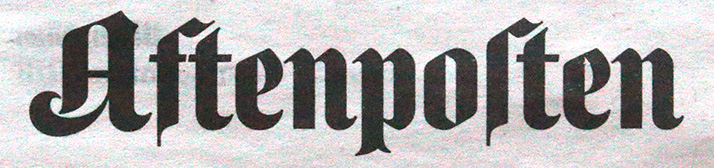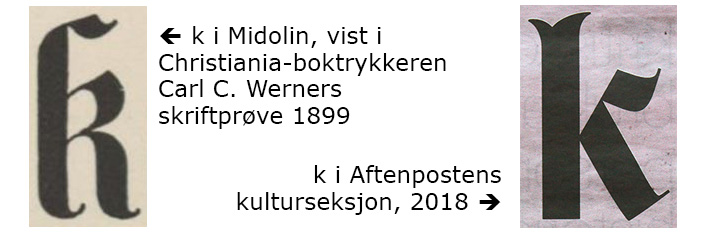
Ane Thon Knutsen disputerte for sin doktorgrad med tittelen over, 18. juni 2019 på Kunsthøgskolen i Oslo. Doktorgraden er av kategorien «Kunstnerisk utviklingsarbeid».
Doktorgradsarbeidet tar utgangspunkt i den britiske forfatteren Virginia Woolf, som i 1917 skrev novellen A Mark on the Wall, samtidig som Woolf lærte seg selv å sette tekst med blytyper i sitt eget trykkeri.
Novellen ble ifølge Ane nærmest skrevet fra settekassen og opp, og i doktorgradsarbeidet har hun utforsket hvordan litteraturen er påvirket av typografien.
Ane har som Woolf skapt sitt eget lille boktrykkeri, og som en del av oppgaven har hun håndsatt hele Woolfs novelle med store maskinfreste løse typer og trykt den på 1837 papirark (bildet). En annen likhet mellom Woolf og Thon Knutsen er deres stilling som kvinner i et (tidligere) mannsdominert fag.
Ved å klikke på en svart hånd øverst til venstre på skjermbildet på hennes nettsted kan man se trykkeprosessen og få tilgang til en 30 min. lydbok hun har spilt inn.
Thon Knutsen er utdannet grafisk designer og hennes mastergrad var også knyttet til boktrykket – som er den tradisjonelle betegnelsen på setting og trykking med løse typer. Dette tradisjonsrike håndverket kalles nå, også i Norge, for «letterpress». Anes praksis plasseres mellom grafisk design og konseptuell boktrykkerkunst.
Ane Thon Knutsen er en entusiastisk utforsker av boktrykkteknikken og typografien – så gratulerer som den første doktor i boktrykk!
Aftenposten endret 6. nov. 2018 sitt design og justerte samtidig sitt 158 år gamle avishode. Aftenposten-logoen er nå mer i tråd med originalen fra 1860-tallet.
I forbindelse med dette arbeidet engasjerte Aftenposten to utenlandske avisdesignere. Verken disse eller avisas ledelse var kjent med bakgrunnen til skrifttypen i det karakteristiske avishodet. I Aftenposten 3. november heter det at den nærmest er ukjent, og kan spontant ha blitt spikket til i tre på stedet, av tyske trykkere.
Dette er ikke riktig, men også forståelig. Denne skriften var i alminnelig bruk i siste halvdel av 1800-tallet, men er deretter gått helt ut av bruk.
Skriften heter Midolin, og ble tegnet av den franske kalligrafen Jean Midolle på 1830-tallet. Det tyske skriftstøperiet Haenel støpte den som trykkskrift på 1840-tallet og solgte matrisene til andre skriftstøperier, noe som ga den stor utbredelse. I store størrelser kan den ha blitt solgt som treskrift. Midolin var vanlig også i Norge, der man ser den brukt som kontrast til den vanlige frakturskriften, i titler og i overskrifter.
Midolin er en hybrid skrift: den blander trekk fra gotisk og antikva skrift, i tillegg til å ha noen helt særegne former - bl.a. A-en i Aftenposten.
Aftenposten i papirversjon har to seksjoner på hver sin rygg. Kulturseksjonen er nå prydet med en k som Aftenposten har forsøkt å tegne i stil med Aftenposten-logoen. Men fordi de ikke har kjent til Midolin-skriften, har dette ikke falt heldig ut. Jeg viser i illustrasjonen først k i den originale Midolin, så Aftenpostens mer kantete, harde k. Denne harmonerer ikke godt med Aftenposten-logoens bokstaver, og burde tegnes om.
Oppdatering: Kulturdelen av Aftenposten med den omtalte k ble nedlagt våren 2019.
Gunnar Lilleng er fra tidligere en feiret bokkunstner (han fikk Bokkunstprisen i 1983). I oktober og november 2018 ble hans glemte typografiske eksperimenter stilt ut i Galleri Grafill i Oslo.
Lilleng er utdannet typograf. På slutten av 1950-tallet dro han på haiketur nedover i Europa og havnet tilfeldig i Basel, der han i to omganger var student ved Allgemeine Gewerbeschule under den berømte typografiteoretikeren Emil Ruder.
– Skrift som informasjon og dekor
– Stefan Ellmer med skrift-stunt
– Pressemuseet Fjeld-Ljom, Røros